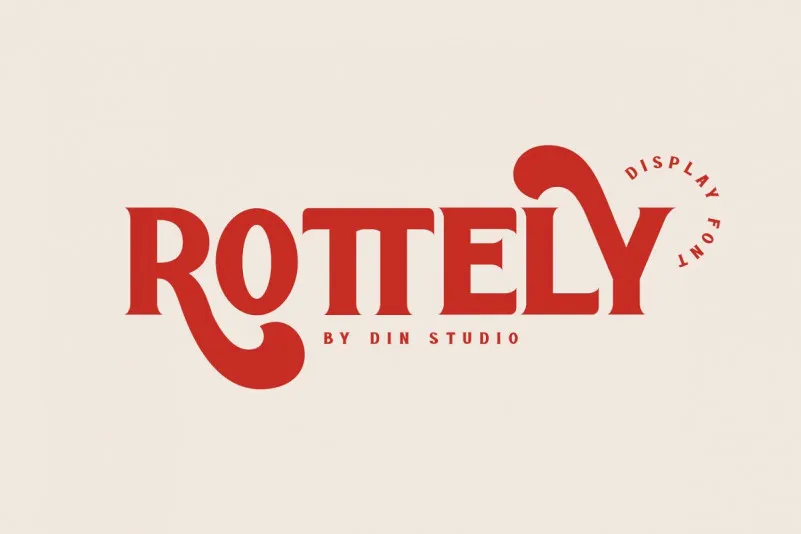
Rottely Display Font – Download Grátis
Descubra a elegância arquitetônica das letras maiúsculas com Rottely Display Font. Inspirada nas formas sofisticadas dos caracteres antigos e combinada com uma aparência moderna, esta fonte exibe linhas reticentes que curvam com um toque de charme em cada letra. Perfectamente projetada para branding e logotipos, essa elegante fonte também é ideal para impressão em camisetas e design gráfico diversificado. Não apenas belas e sofisticadas, Rottely apresenta uma aparência moderna e marcante, certificando-se de ser a escolha perfeita para personalizar o seu mundo visual. Caso seja um designer que busca estilizar sua marca com estilo único, não hesite em explorar esta fonte incrível. Com Daikian como criador, Rottely Display Font traz uma combinação única e irresistível de elegância e modernidade, tornando-a a escolha perfeita para quem deseja deixar uma impressão forte e imediata. Seja você um iniciante ou um mestre do design gráfico, certamente encontrará neste fonte uma ferramenta poderosa para moldar e criar experiências visuais memoráveis. Não hesite em experimentar Rottely Display Font; ela não apenas será sua melhor escolha, mas também seu novo amigo de trabalho ao se juntar a você no desafio de transformar ideias em arte visual.